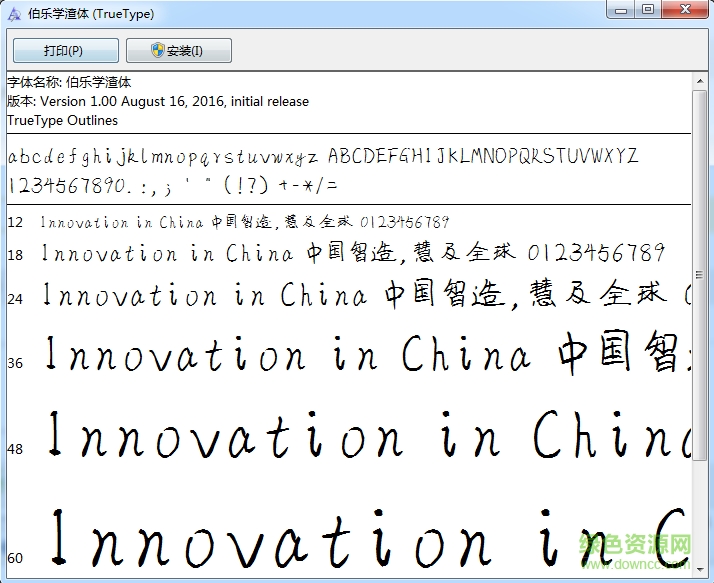
伯樂(lè)學(xué)渣體是一款典型的手寫(xiě)體字體,看似不規(guī)則的筆畫(huà)但有著自己的獨(dú)特,感受學(xué)渣的韌性和不言棄的堅(jiān)持,喜歡的普就來(lái)綠色資源網(wǎng)嘗試吧!
伯樂(lè)學(xué)渣體作為一款撥了字體,同是手寫(xiě)風(fēng)格,字體完整支持中英文書(shū)寫(xiě),有著合適的寬度和高度,常用于平面設(shè)計(jì)、名片設(shè)計(jì)、海報(bào)設(shè)計(jì)、排版印刷等行業(yè),有著不錯(cuò)的觀賞體驗(yàn)。
伯樂(lè)學(xué)渣體 Version 1.00 August 16, 2016, initial release字體(字體家族名稱:伯樂(lè)學(xué)渣體;字體風(fēng)格樣式名稱:伯樂(lè)學(xué)渣體),共有6917個(gè)字符。